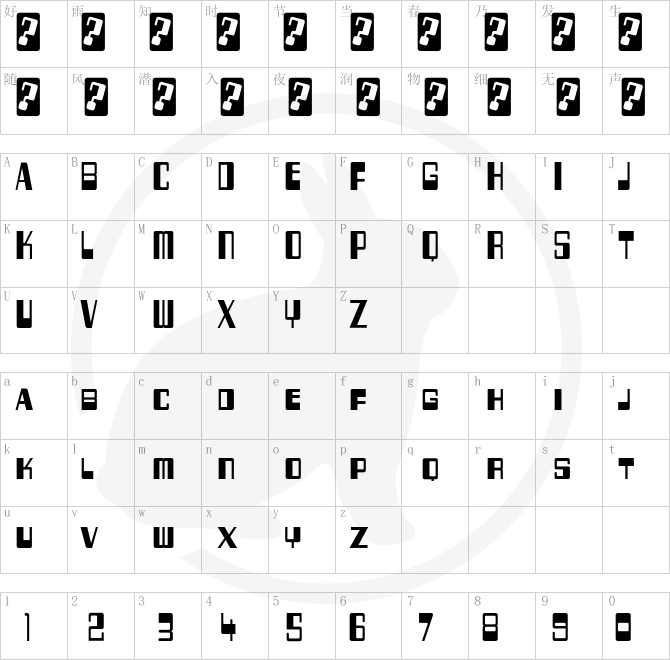
Two Fifty Six Bytes.otf字体下载,这款字体结构工整、笔画清晰,兼顾美观与易读性,适用于标题、正文、海报、包装、LOGO 等多种场景。字形优雅稳定,风格百搭耐看,适配日常排版与创意设计,让文字呈现更舒适、更具质感。Two Fifty Six Bytes.otf字体下载一笔一画,皆是细节,以均衡的比例、流畅的线条打造舒适视觉体验,字形端正大气,风格简约现代。无论是商业设计、品牌宣传还是日常排版,都能轻松驾驭,让文字更有格调与力量。Two Fifty Six Bytes.otf字体下载字体下载。